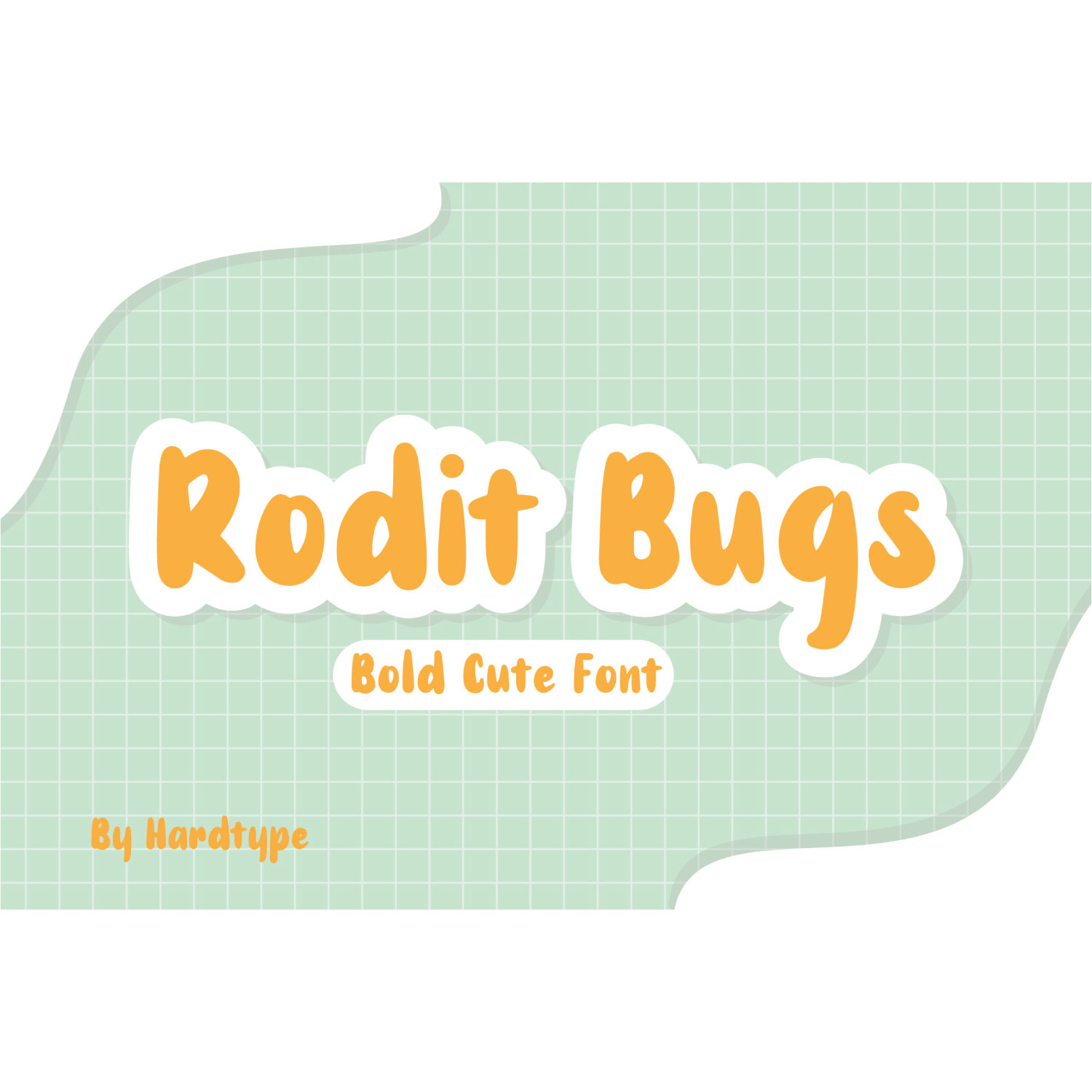
Rodit Bugs Font
Designed by Richardwibi
About Rodit Bugs
Rodit Bugs font. adalah font yang terlihat lucu, gemuk, dan menyenangkan. font ini bisa di gunakan untuk kebutuhan craft, design sosial media, kartu ucapan dan kebutuhan lainnya. selamat berkreasi dengan rodit bugs font :)